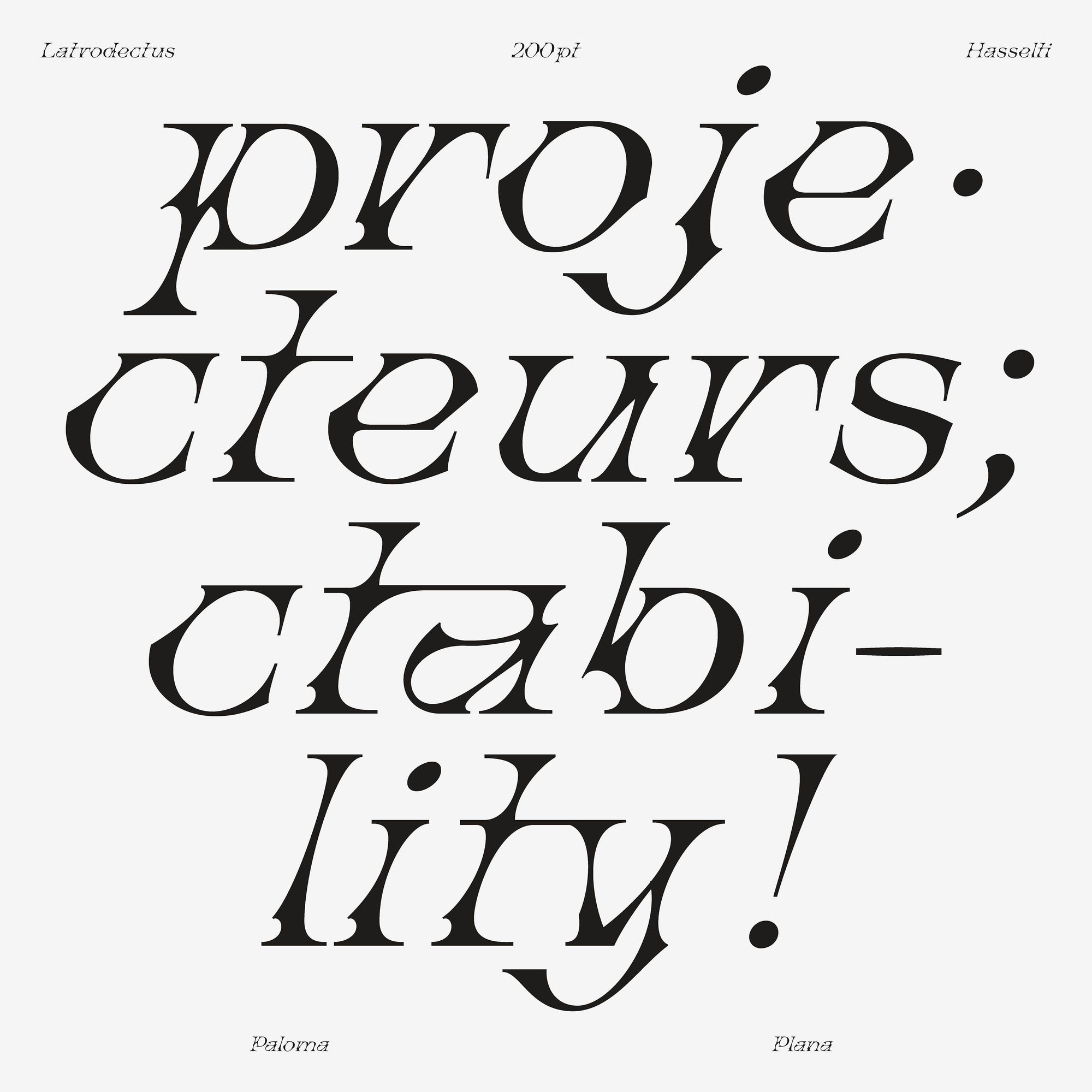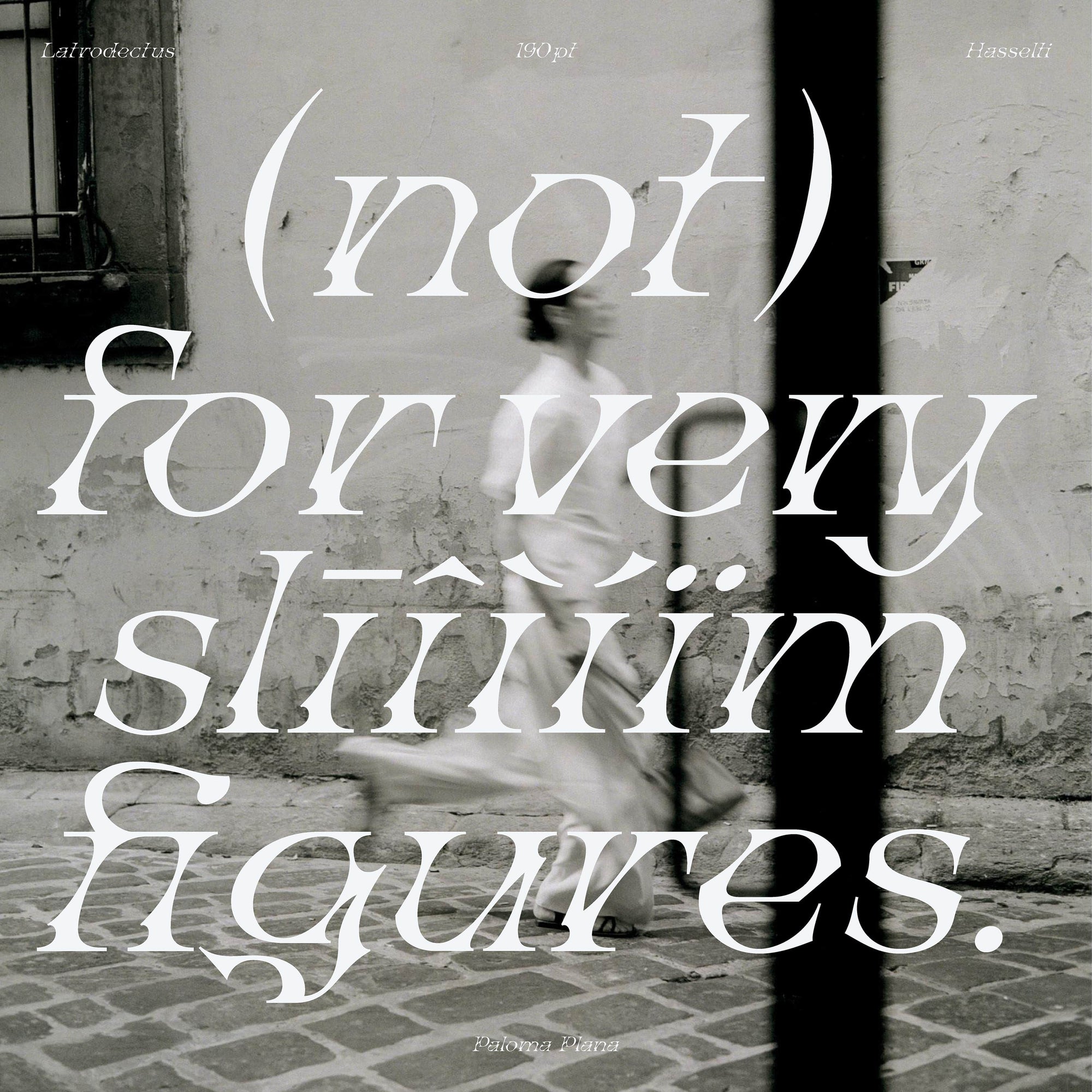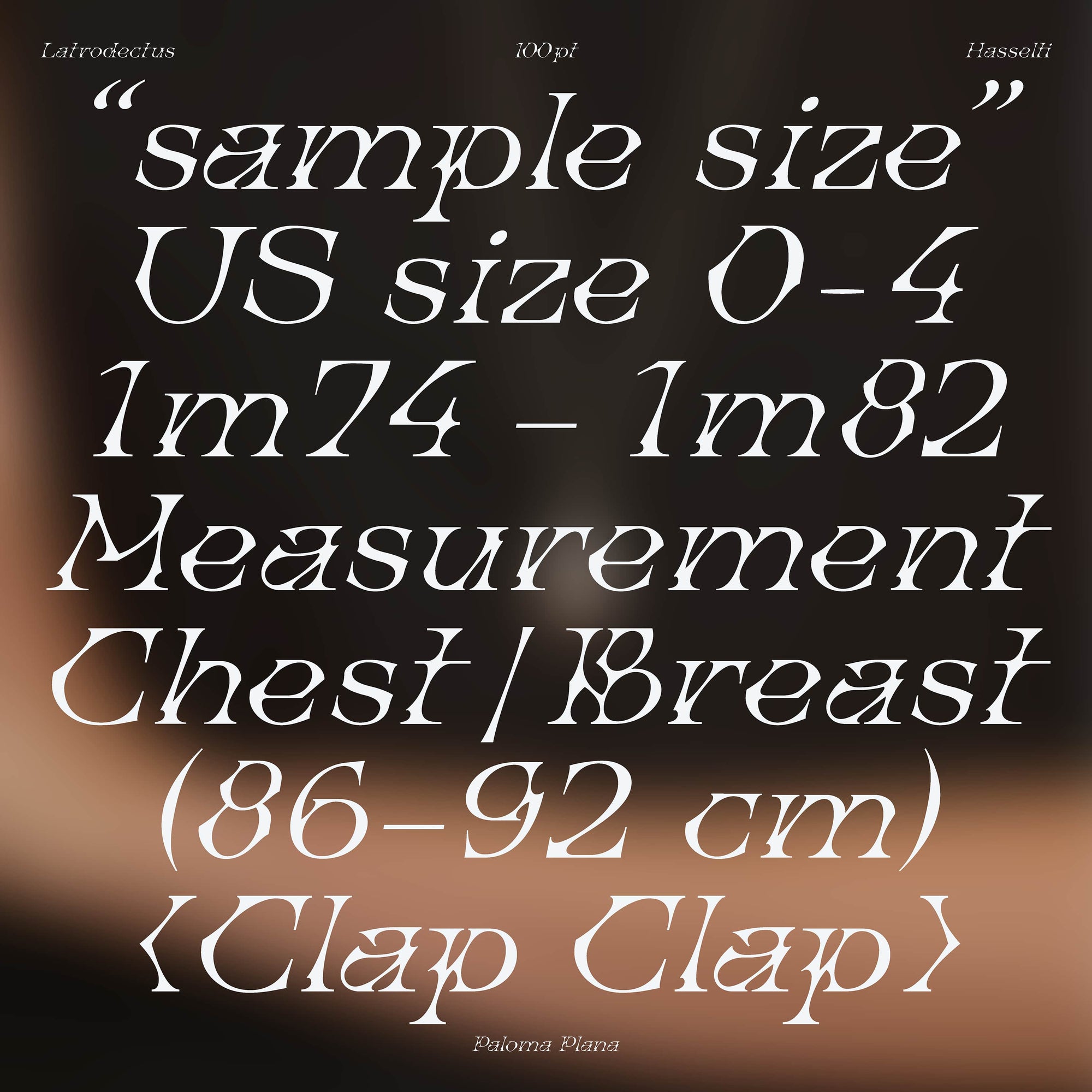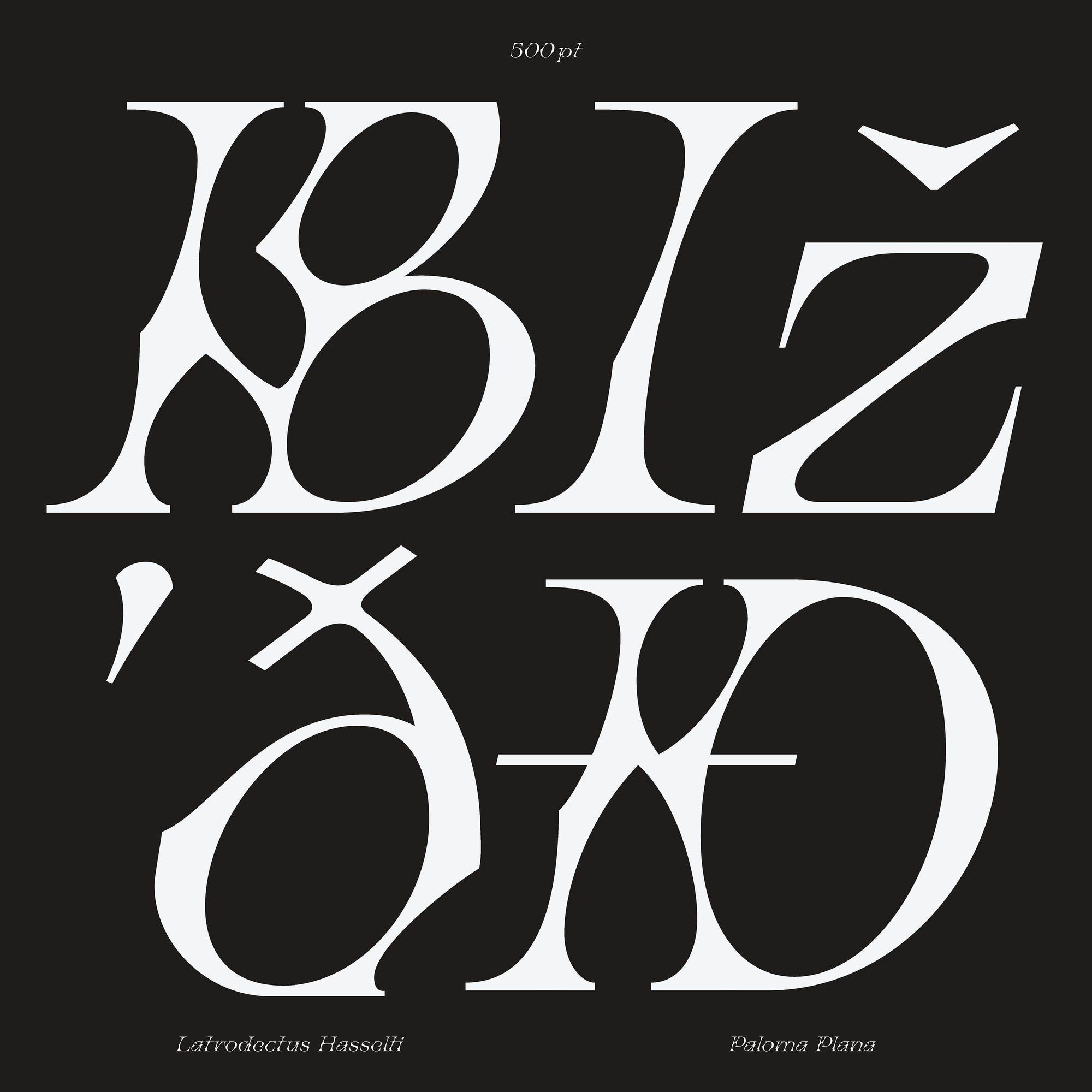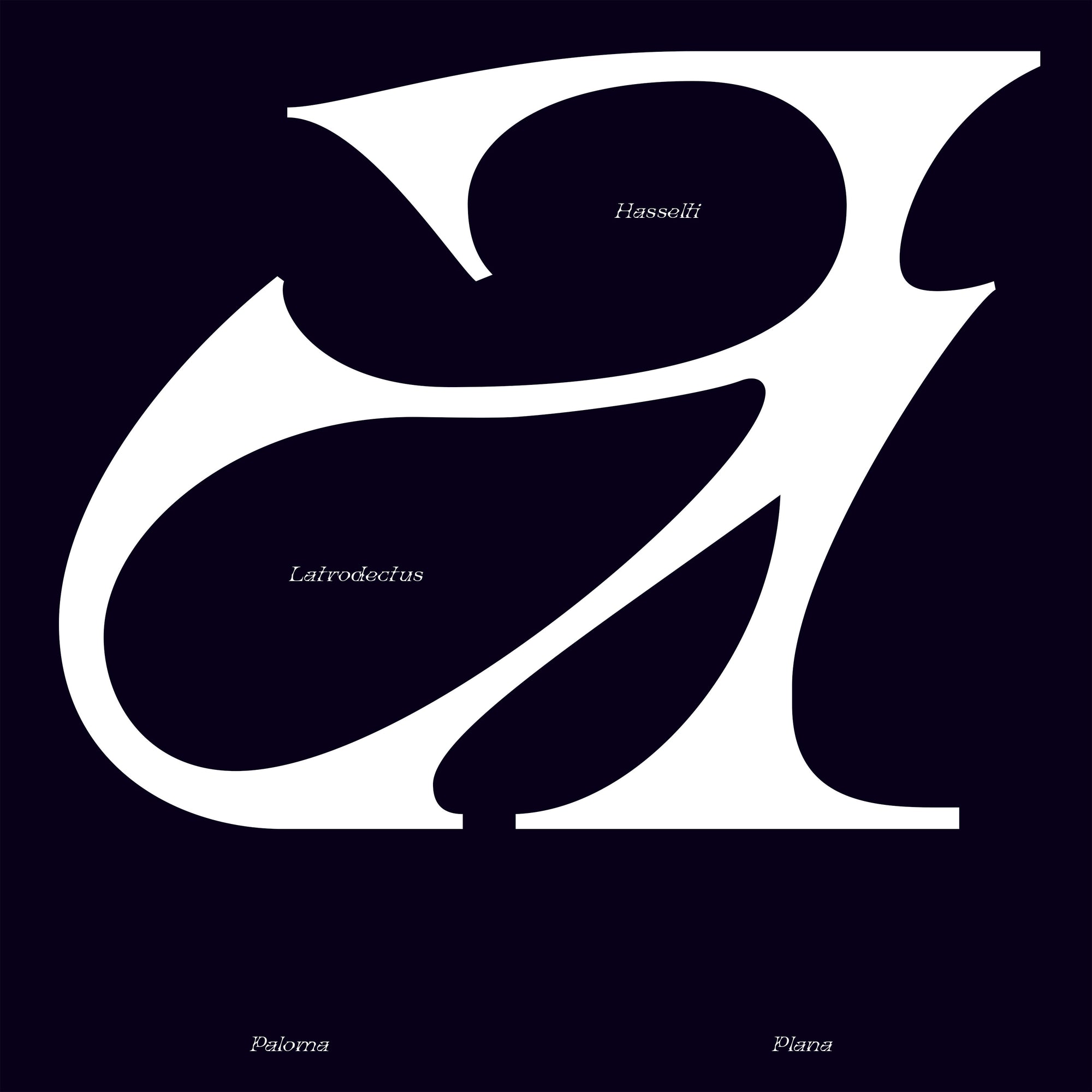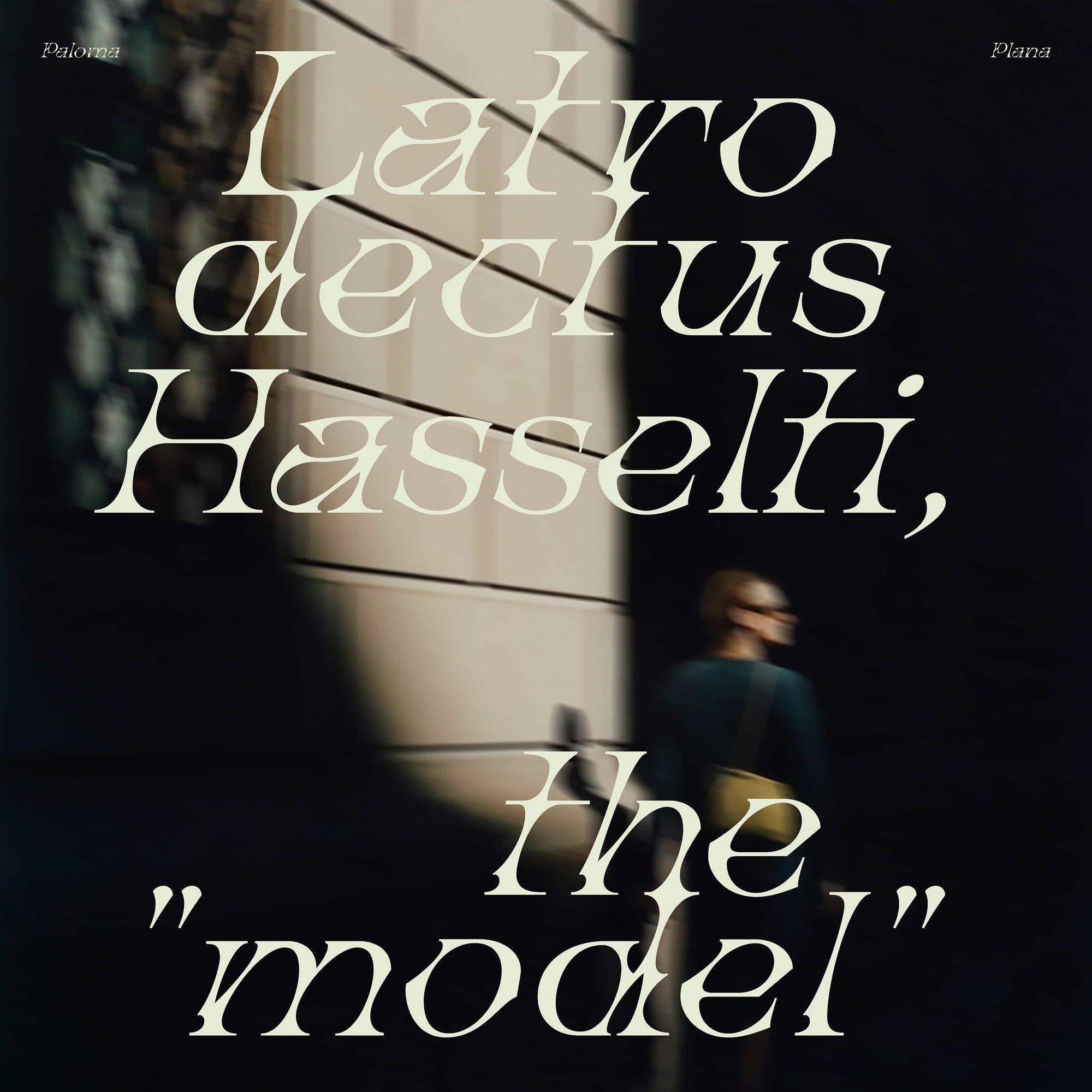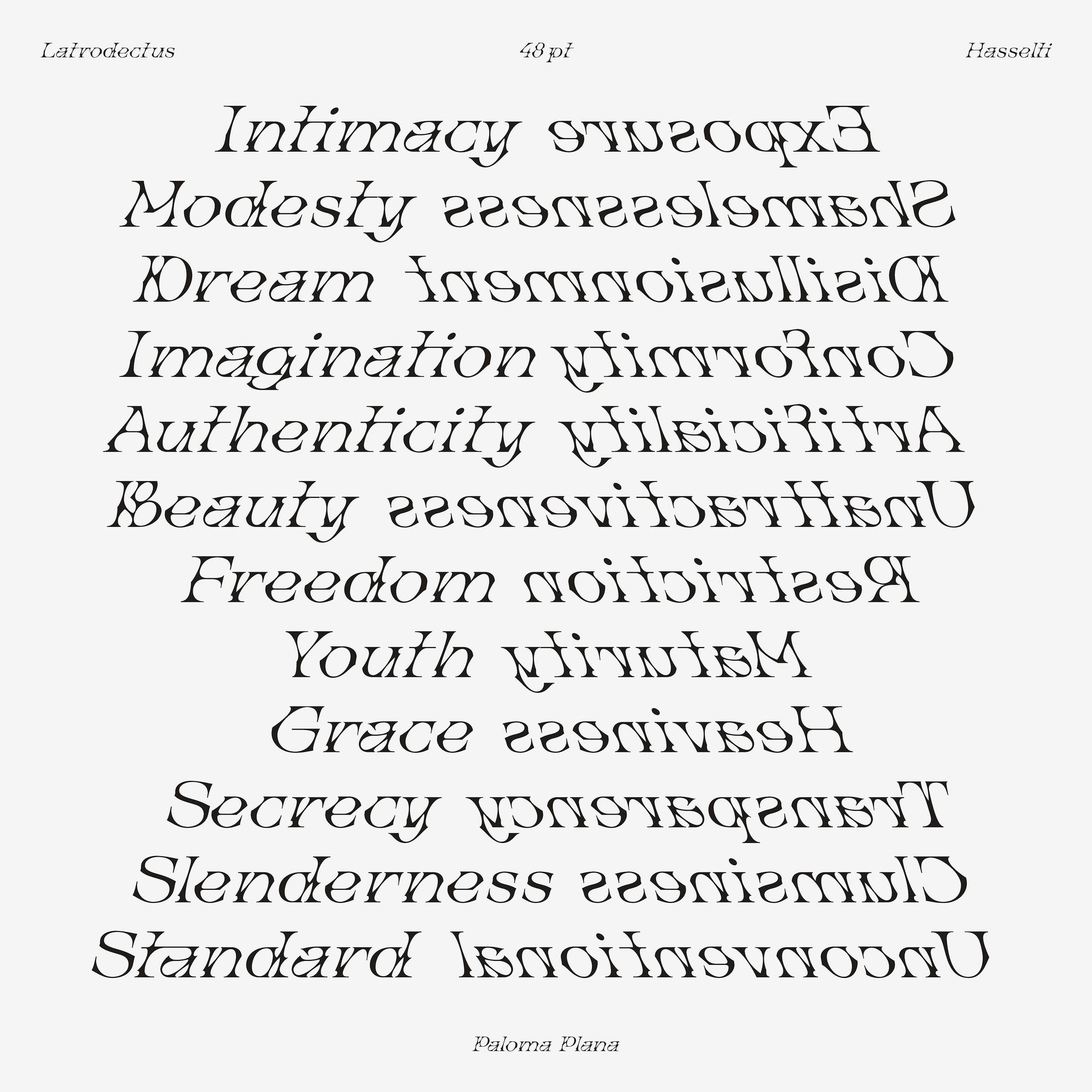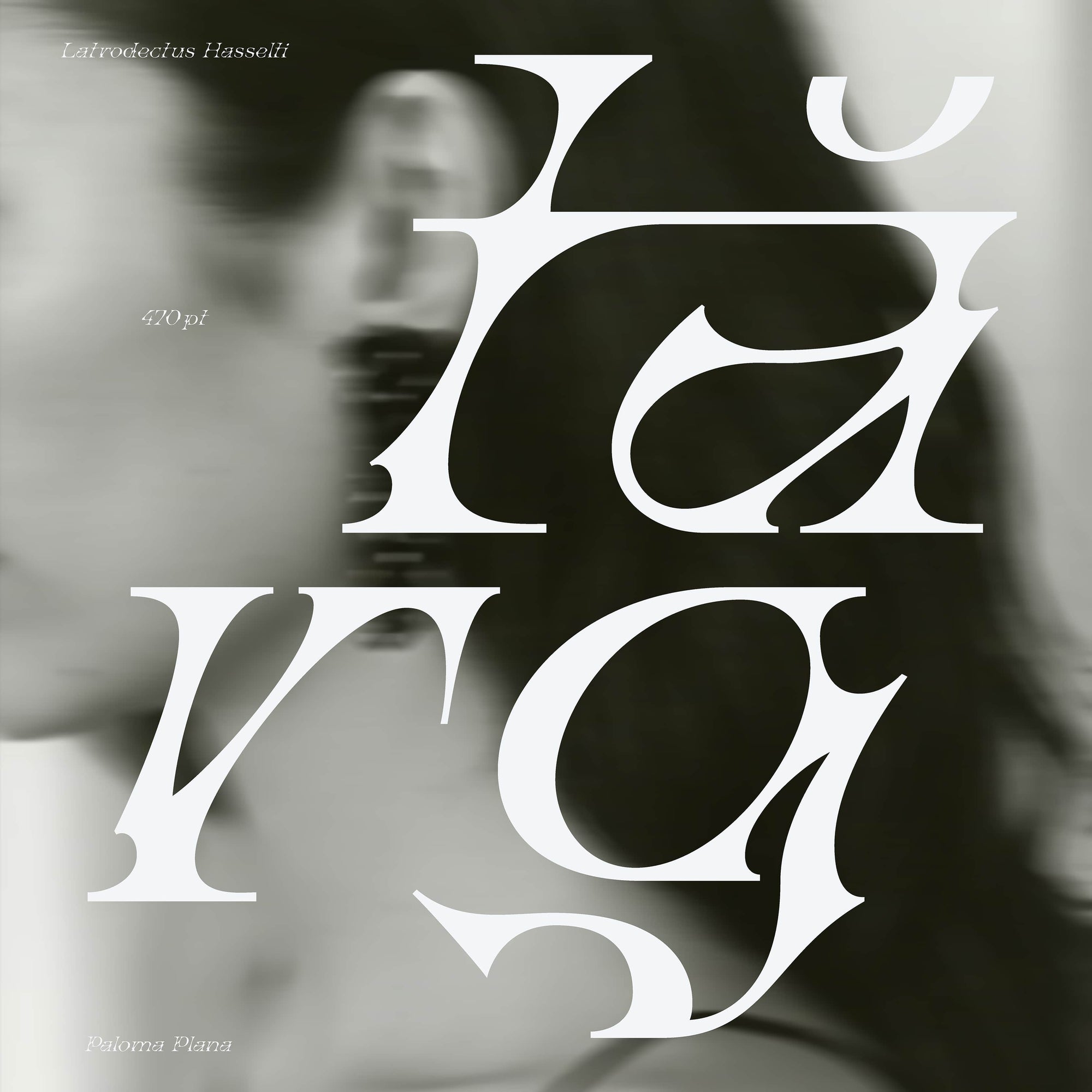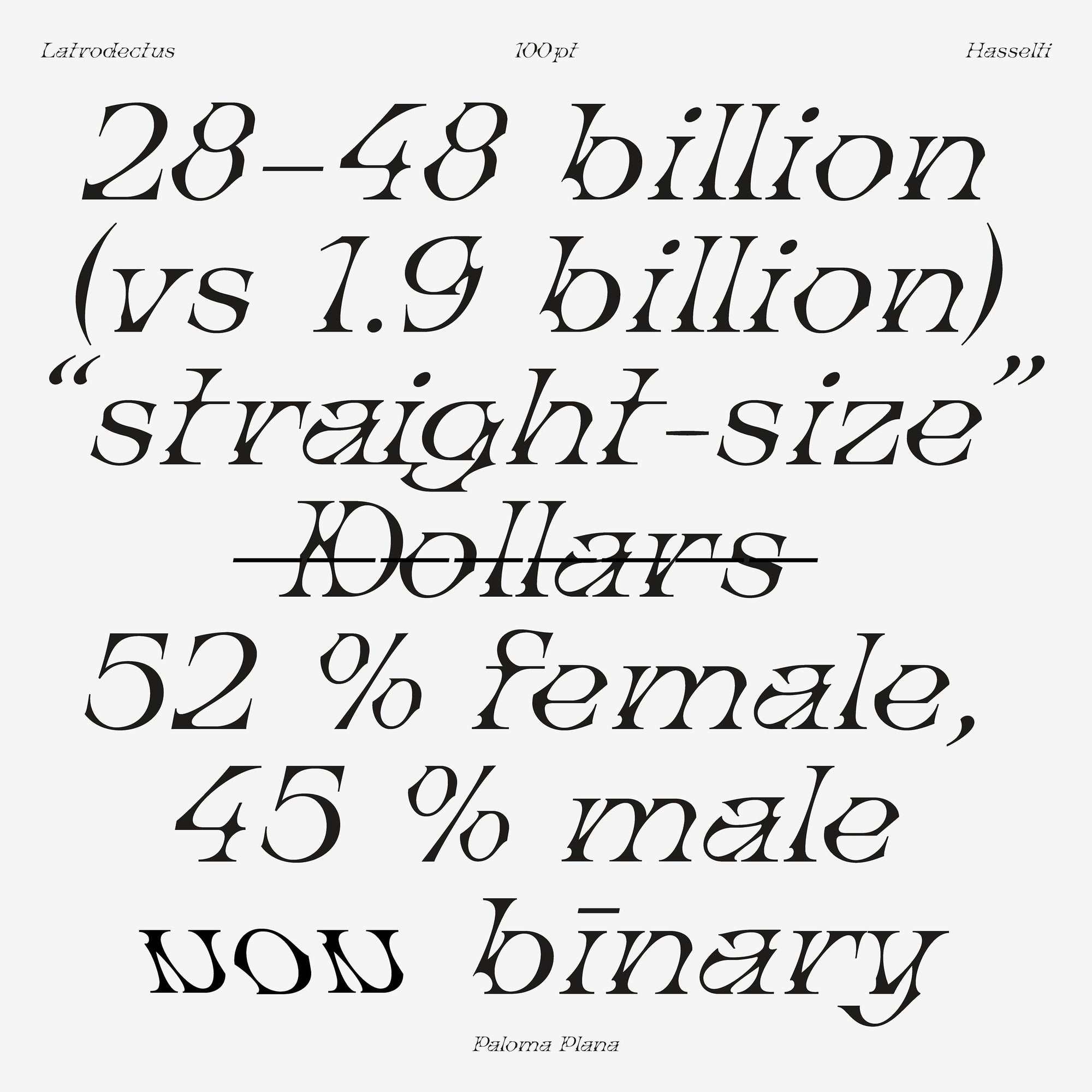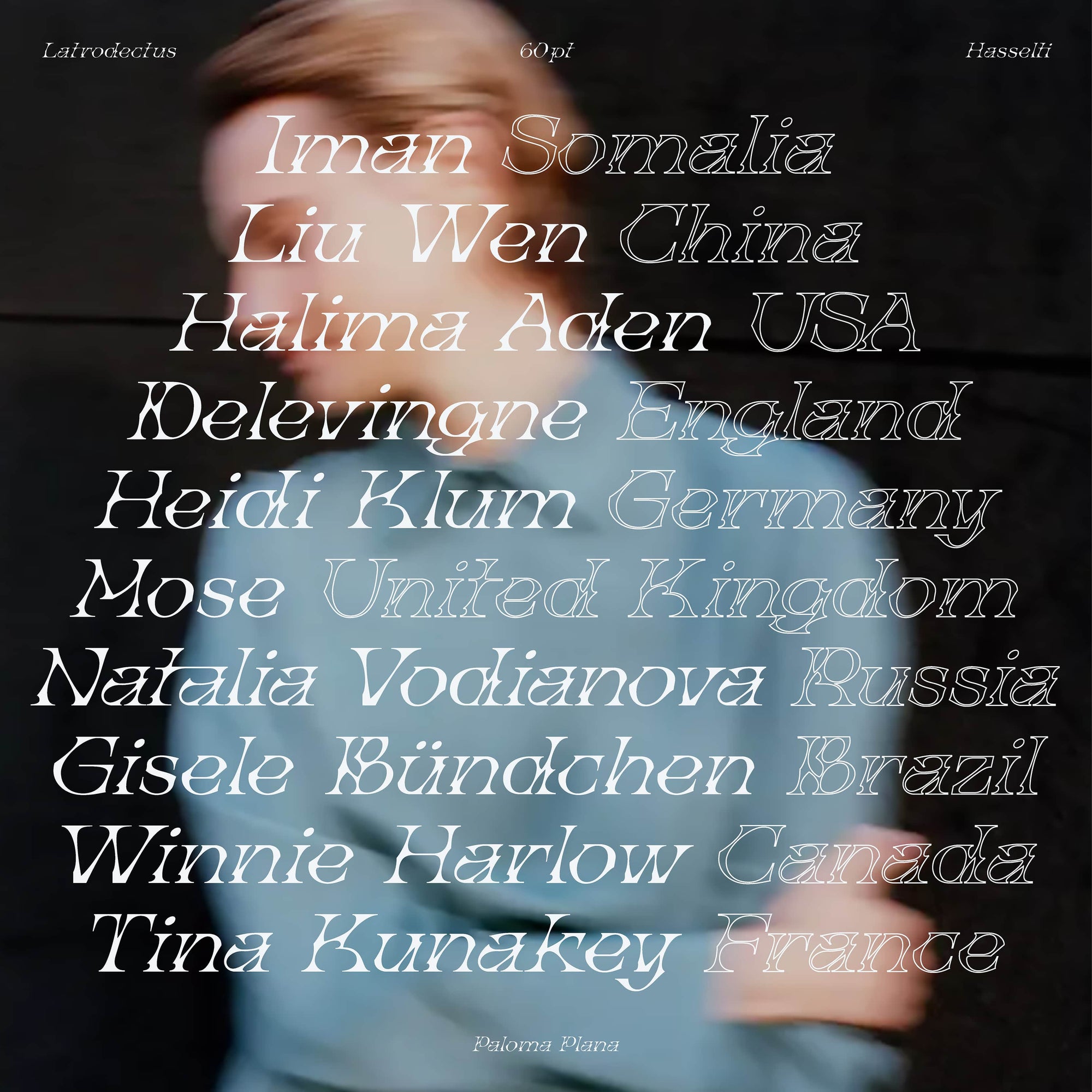
Latrodectus Hasselti Schriftart
Latrodectus Hasselti ist eine experimentelle Display-Schriftart, die 2020 von Paloma Plana entworfen wurde. Sie ist charakterstark, interessant in der Anwendung und scharf ausdrucksstark. Mächtig in ihrer Einzigartigkeit und entschlossen unkonventionell, zeichnet sie sich durch einen 10°-Neigungswinkel und starke Kontraste zwischen dicken und dünnen Strichen aus. Die Schriftart umfasst derzeit 365 Glyphen: das lateinische Alphabet, diakritische Zeichen, 64 Ligaturen, Satzzeichen, Zahlen und einige versteckte Überraschungen. Sie ist so konzipiert, dass sie je nach Verwendung als dünn wahrgenommen wird.
Merkmale
• 365 Glyphen
• Zeichensatz: Lateinisch-Europäisch
• Diakritische Zeichen
• Ligaturen
• Zahlen
• Satzzeichen
• Symbole
• Währung
• Mathematik